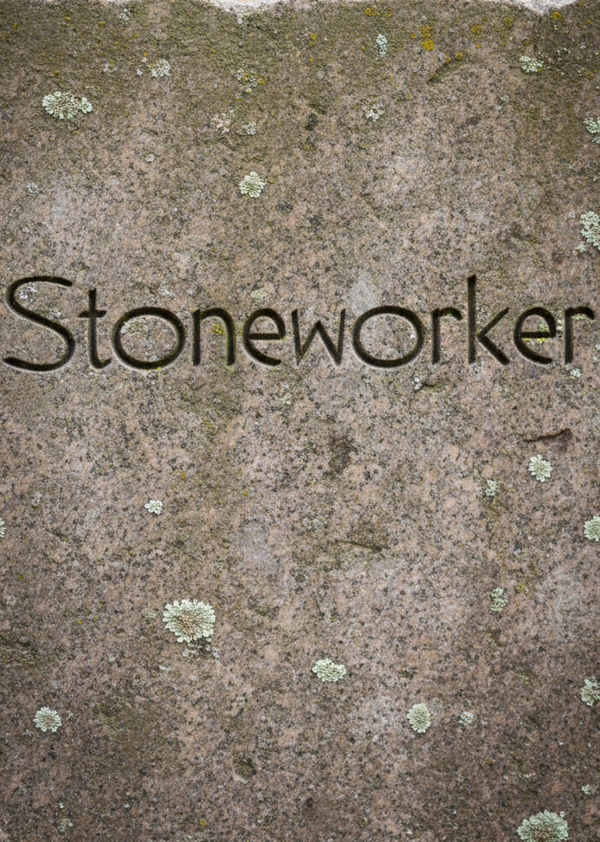
stoneworker font
stoneworker — брутальный и пластичный гротеск
с гипертрофированными круглыми знаками, напоминающими речные валуны на фоне каллиграфически выверенных прямых штрихов
штрих, вдохновленный основами каллиграфии